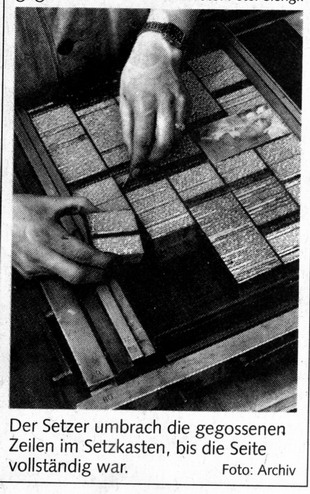
Umbruch im Setzkasten?
Gut 30 Jahre nach Ende der Bleisatz-Ära gibt es offensichtlich
immer weniger Menschen, die noch wissen, wie früher eine Tageszeitung
produziert wurde. Anders ist die Bildunterschrift aus der Beilage der
»Braunschweiger Zeitung« vom 18. Februar 2012 (65 Jahre Braunschweiger
Zeitungsverlag) nicht zu erklären. Den Setzer hätte ich sehen mögen,
der seine Zeilen im Setzkasten umbrochen hätte. Natürlich zeigt das Bild
einen Metteur, der seine Linotype-Zeilen im Schließschiff umbricht.
Freut euch doch, dass der Bleisatz überhaupt noch Erwähnung findet! Hätte da gestanden, dass da ein »Metteur Linotype-Zeilen im Schließschiff umbricht« wäre es vielleicht richtig gewesen, aber wer außer einer Handvoll Fachleute soll diesen Satz überhaupt verstehen?*
*Was jetzt natürlich nicht heißen soll, dass man absichtlich Fehler einbauen sollte.
Freut euch doch, dass der Bleisatz überhaupt noch Erwähnung findet!
Nach der Devise: "Hauptsache, der Name ist richtig geschrieben"?
Jeder sachliche Fehler in einem Zeitungsartikel steht dafür, was der Journalist und die Redaktion von ihrer eigenen Arbeit halten. Es kommt überall auf das Detail an, wir freuen uns ja heute auch nicht über unausgeglichene Versalzeilen nach dem Hinweis: Freu dich, daß die richtigen von den 26 Buchstaben da stehen, welche und wie, ist doch egal.
So tot wird der Bleisatz noch lange nicht sein, daß wir uns darüber freuen, daß da nicht Eisensatz steht.
Freut euch doch … überhaupt …
Es geht hier immerhin um die Jubiläumsschrift enes Zeitungsverlages, nicht einer Großbäckerei. Die haben also keine Ahnung von ihren eigenen Wurzeln. Da ist nix mit freuen, da ist nur fremdschämen. :neenee:
Vielleicht haben die wirklich so gesetzt? Sie wussten es einfach nicht besser …
Es ist ein falscher Fachbegriff verwendet worden, ja. Ihr (drei) reagiert darauf heftig, weil ihr mit der Materie vertraut seid. Auch klar. (Ich reagiere heftig bei falschen Eszett-Einsätzen. Hat halt jeder so sein Steckenpferd.)
Aber es ist auch nur Bleisatz. Eine von hunderten überflüssig gewordenen Techniken. Ob sie in der Beilage gut gewürdigt wurde, kann ich nicht beurteilen – ich habe sie ja nicht gelesen. Aber nun wegen einem falschen Fachbegriff gleich wieder den Kulturverfall durch »Unkenntnis unserer Wurzeln« ausrufen zu wollen, steht eben auch wieder in keinem Verhältnis. Ich hätte es spannender gefunden, mehr aus der Beilage zu sehen, als nur den Hinweis auf den falschen Fachbegriff.
Warum diese Schärfe? Hier hat niemand den »Kulturverfall« ausgerufen!
Und in 30 Jahren steht dann vielleicht unter einem Foto eines Kommunikationsdesigners
am Mac: »Online-Journalist beim Bedienen einer Kaffeemaschine...«
Warum diese Schärfe? Hier hat niemand den »Kulturverfall« ausgerufen!
Das schwingt halt immer in Euren Beiträgen über den Bleisatz und den Aussagen über dessen Wichtigkeit mit. Aber okay, wenn es keinen Grund zu Schärfe gibt, werde ich auch keinen suchen.
Insofern sag ich auch lieber nix mehr – auch nicht zu dem Kaffeemaschinen-Vergleich ... ;-)
Womit Du natürlich doch etwas dazu gesagt hast, wie ich schmunzelnd feststelle – aber ich will auch nichts gesagt haben.